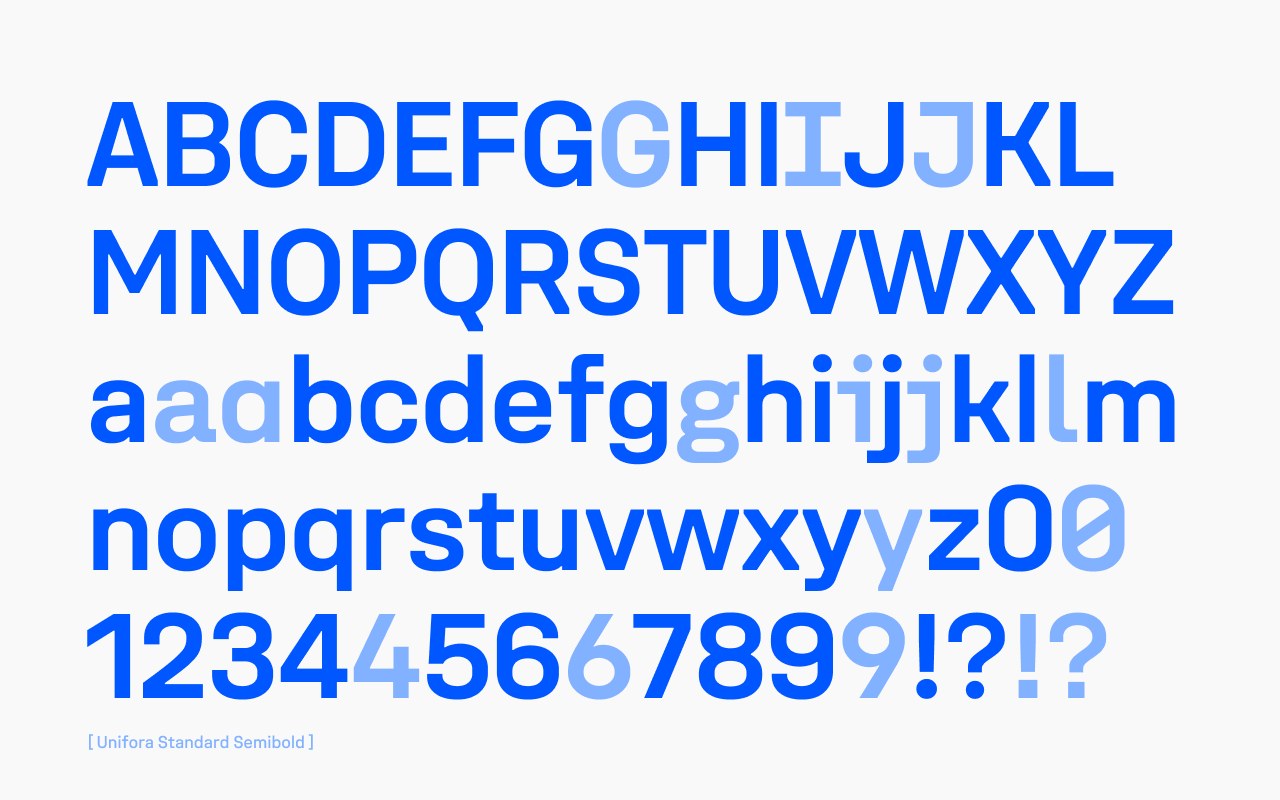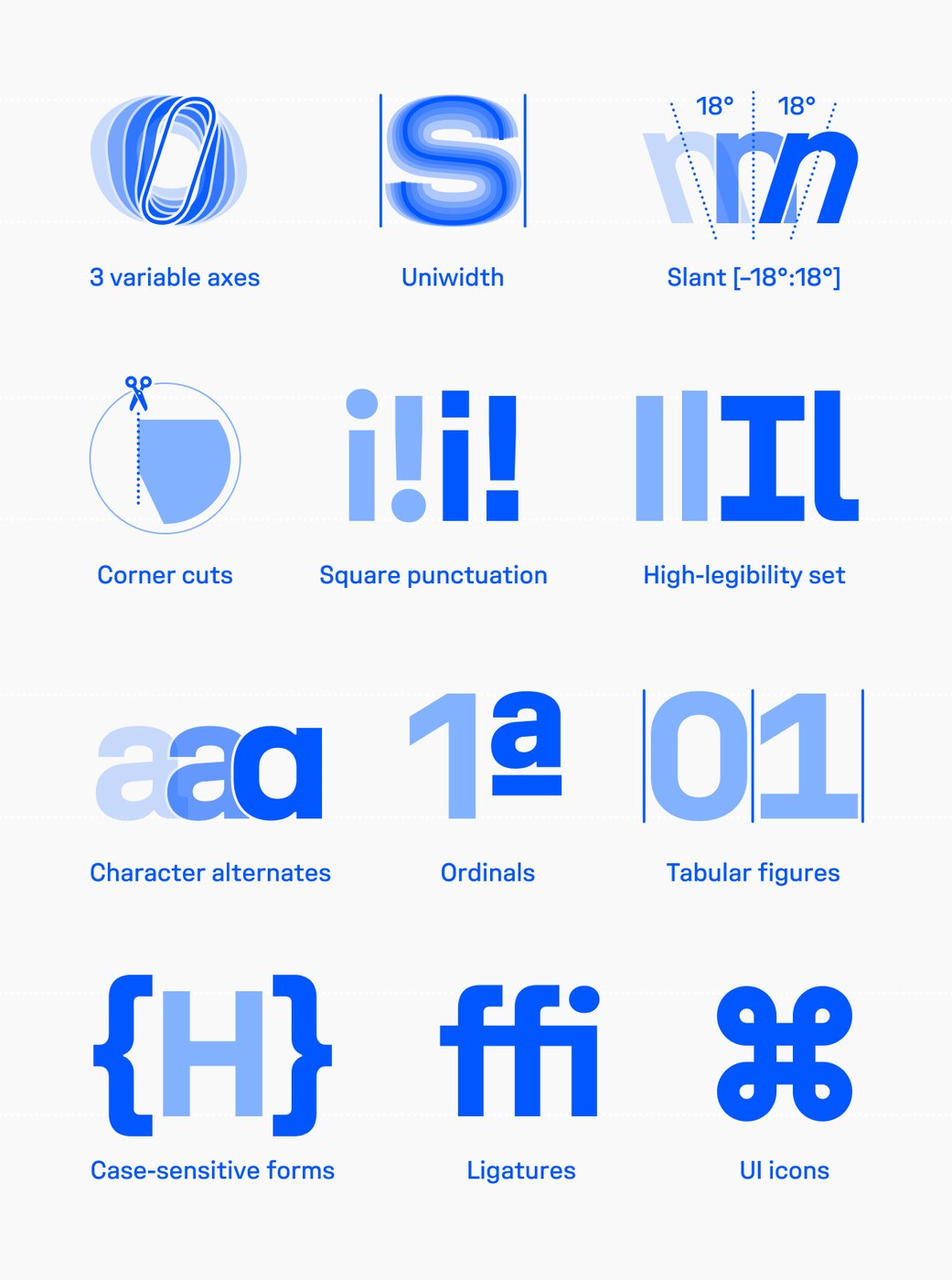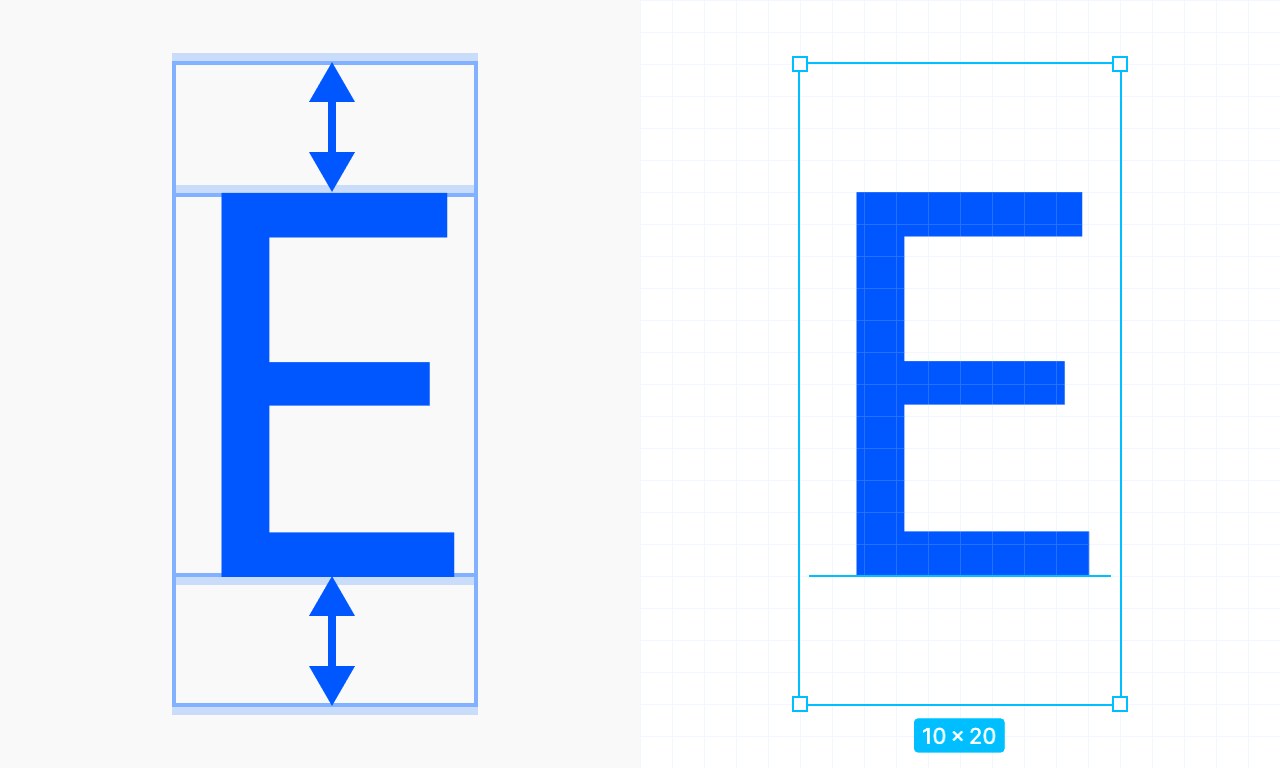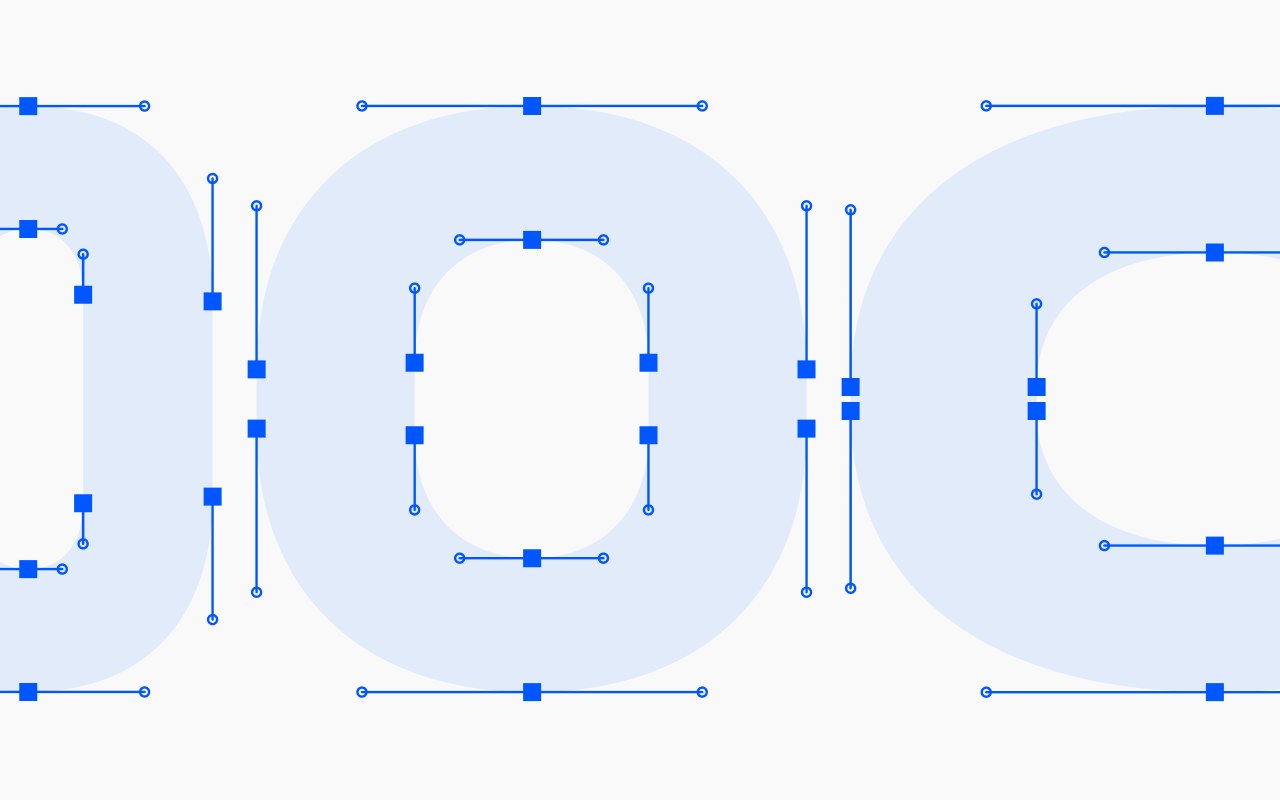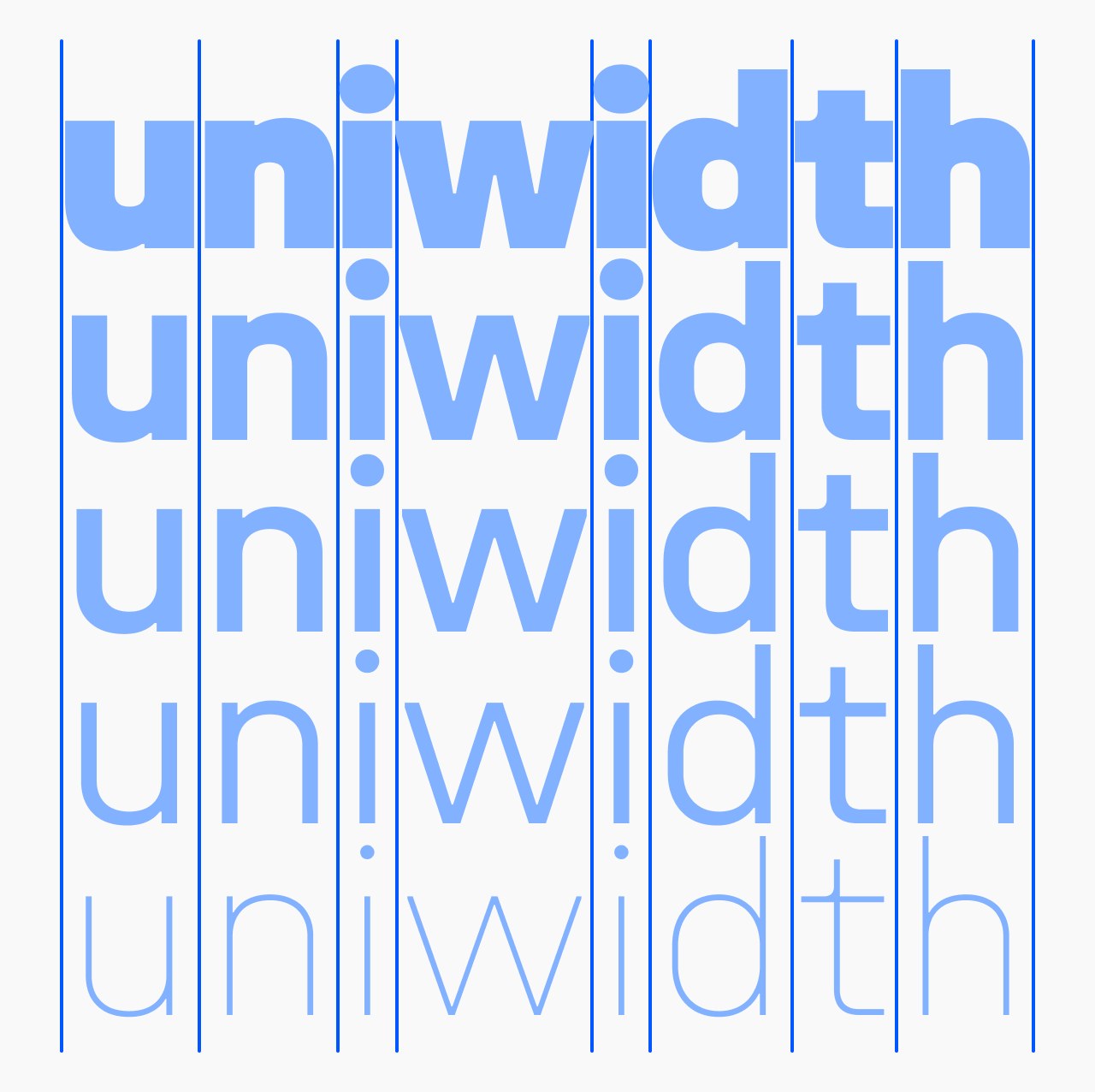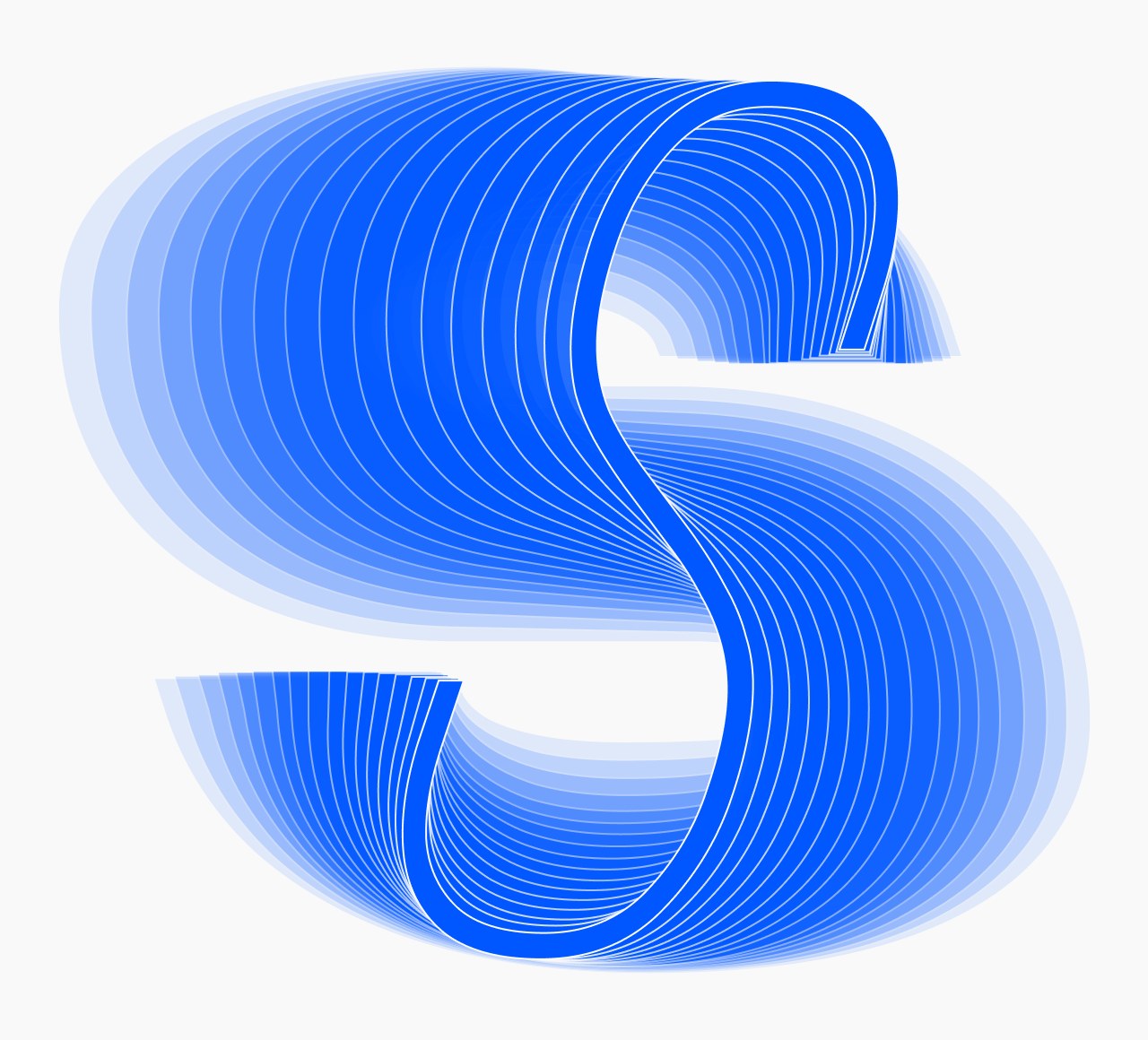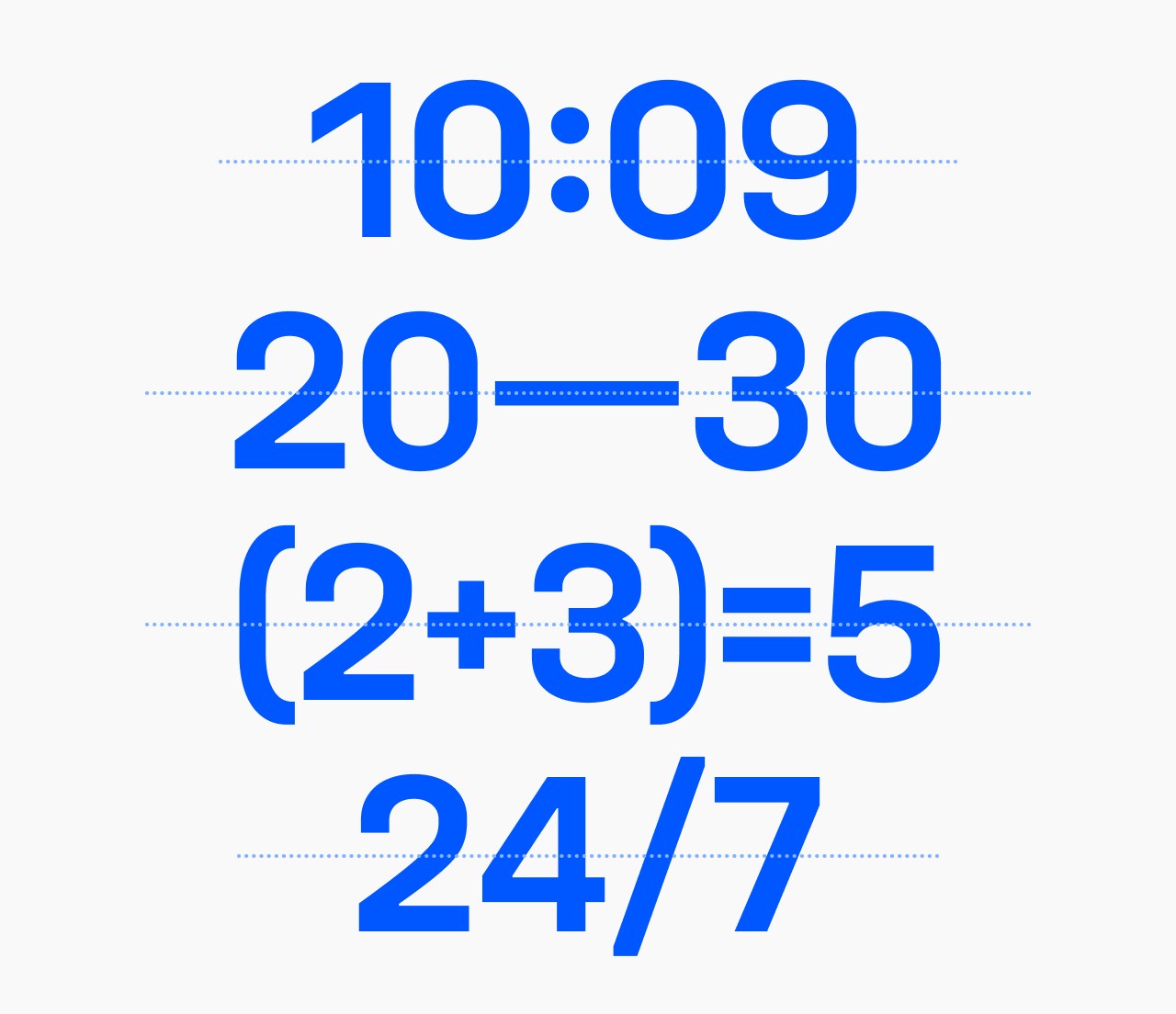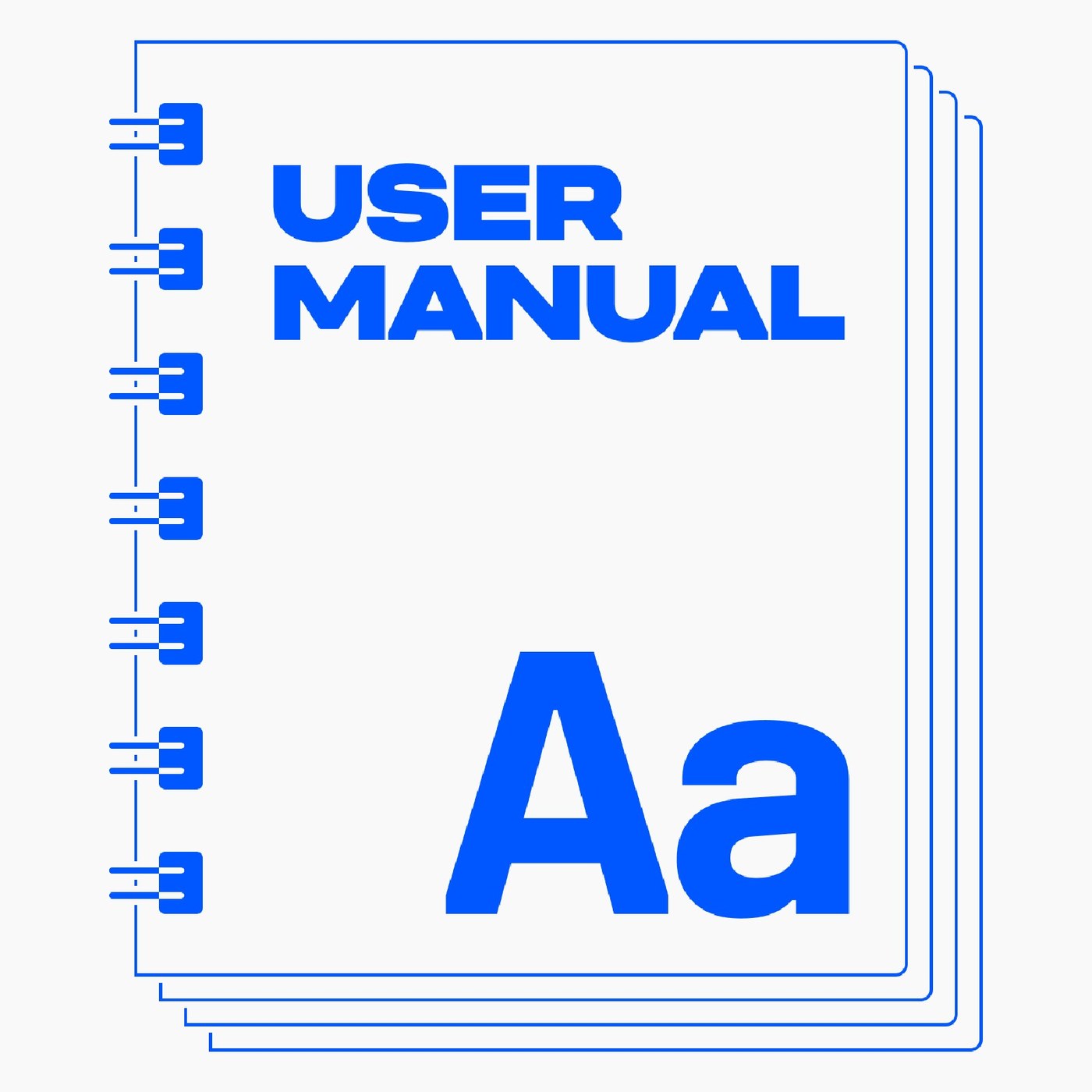
Unifora là một superfamily đến từ Yep! Type Foundry, lấy cảm hứng từ cấu trúc logic của font DIN huyền thoại nhưng được nâng cấp toàn diện để “chiến” tốt trên các loại màn hình hiện đại. Mọi ký tự đều được căn chỉnh chuẩn theo pixel grid, giúp hiển thị cực kỳ sắc nét trên mọi trình duyệt mà không lo bị nhòe. Phần cap height cũng được tính toán kỹ để khớp chính xác vào lưới pixel, mang lại sự chỉn chu tuyệt đối cho thị giác.
Điểm “ăn tiền” của bộ font này chính là hệ thống uniwidth. Dù có thay đổi từ kiểu Thin sang Black thì độ rộng của đoạn văn bản vẫn giữ nguyên, không hề làm nhảy layout hay gây hiện tượng reflow. Đây là tính năng cực kỳ hữu ích cho các bảng hiển thị dữ liệu, dashboard tương tác hay hệ thống chỉ dẫn phức tạp. Về mặt thẩm mỹ, các chữ cái mang phong cách hình học công nghiệp rất mạnh mẽ, với những đường cắt góc tinh tế giúp tạo thêm khoảng trống, đảm bảo tính dễ đọc luôn ở mức cao nhất ngay cả trong những giao diện chật hẹp.
Sự chuẩn xác trong kiến trúc Typography
Siêu họ font này sở hữu đầy đủ các kiểu đứng, nghiêng (italic) và cả nghiêng ngược (retalic). Trục nghiêng có biên độ rộng từ -18 đến +18 độ, mở ra không gian sáng tạo linh hoạt cho các hiệu ứng animation trong motion design. Để tối ưu cho việc đọc và tránh nhầm lẫn ký tự, font còn cung cấp bộ tính năng “high-legibility” với các chữ in hoa có chân và số 0 có gạch chéo. Các dấu câu dạng hình vuông cũng có sẵn để đồng bộ hoàn hảo với nét hình học đặc trưng của bộ chữ.
Yep! Type Foundry, một studio tại Lisbon, đã tạo ra một hệ thống font biến đổi (variable font) mang lại khả năng kiểm soát tối đa cho các nhà phát triển. Unifora thực sự là một case study thú vị, chứng minh rằng những font chữ dạng cấu trúc vẫn có thể trở nên cực kỳ mượt mà khi được tối ưu cho môi trường số. Để tìm hiểu kỹ hơn về cách áp dụng vào dự án, các team có thể tham khảo thêm tại hướng dẫn sử dụng trên https://yeptype.com/article/unifora-a-users-manual